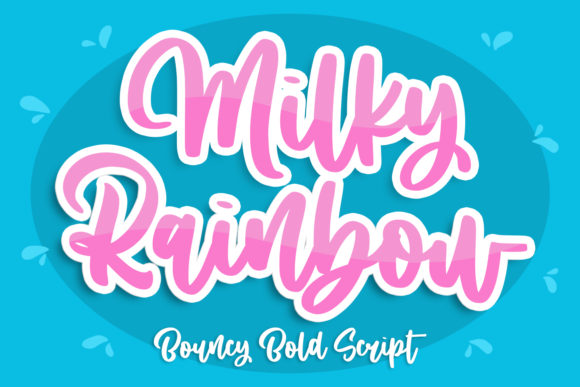
Creativefabrica Milky Rainbow Font
[Creativefabrica] Milky Rainbow Font
Milky Rainbow - это милый и причудливый шрифт.
Он добавит невероятно радостный штрих в ваши проекты.
Добавьте этот красивый шрифт к каждой из своих творческих идей и заметите, как он их выделяет!